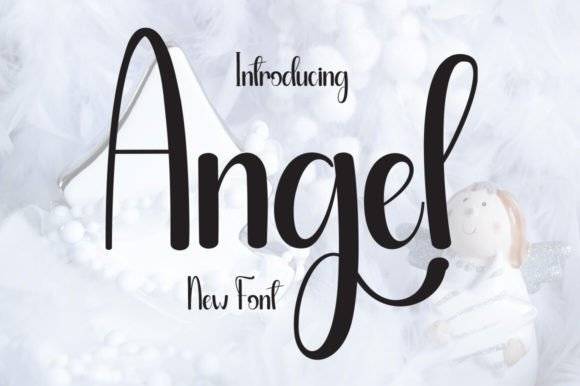
Fonte Angel para artesanato, logotipos e projetos de impressão.
Angel é uma fonte sofisticada, criada para uso em artesanato, desenvolvimento de logotipos e projetos de impressão de alta qualidade. Suas formas refinadas oferecem um equilíbrio perfeito entre estilo e legibilidade, tornando-a uma excelente escolha para identidade visual refinada e papelaria personalizada.
Esta fonte é ideal para criadores em meios digitais e físicos, oferecendo resultados de qualidade profissional em embalagens, identidades visuais corporativas e projetos de design pessoal. Angel se destaca em temas de casamento, rótulos de boutiques e marcas de produtos artesanais.
Sua tipografia elegante garante alta legibilidade, ao mesmo tempo que adiciona um toque de sofisticação a cada composição em que aparece.
- Estilo elegante e atemporal
- Alta legibilidade em todos os tamanhos.
P: Que tipo de fonte é Angel?
A: Angel é uma fonte tipográfica limpa e elegante, criada para logotipos, artesanato e projetos de design gráfico de alta qualidade.
P: Posso usar para convites de casamento?
A: Sim, seu estilo elegante o torna ideal para convites, cardápios, sinalização e artigos de papel para eventos.